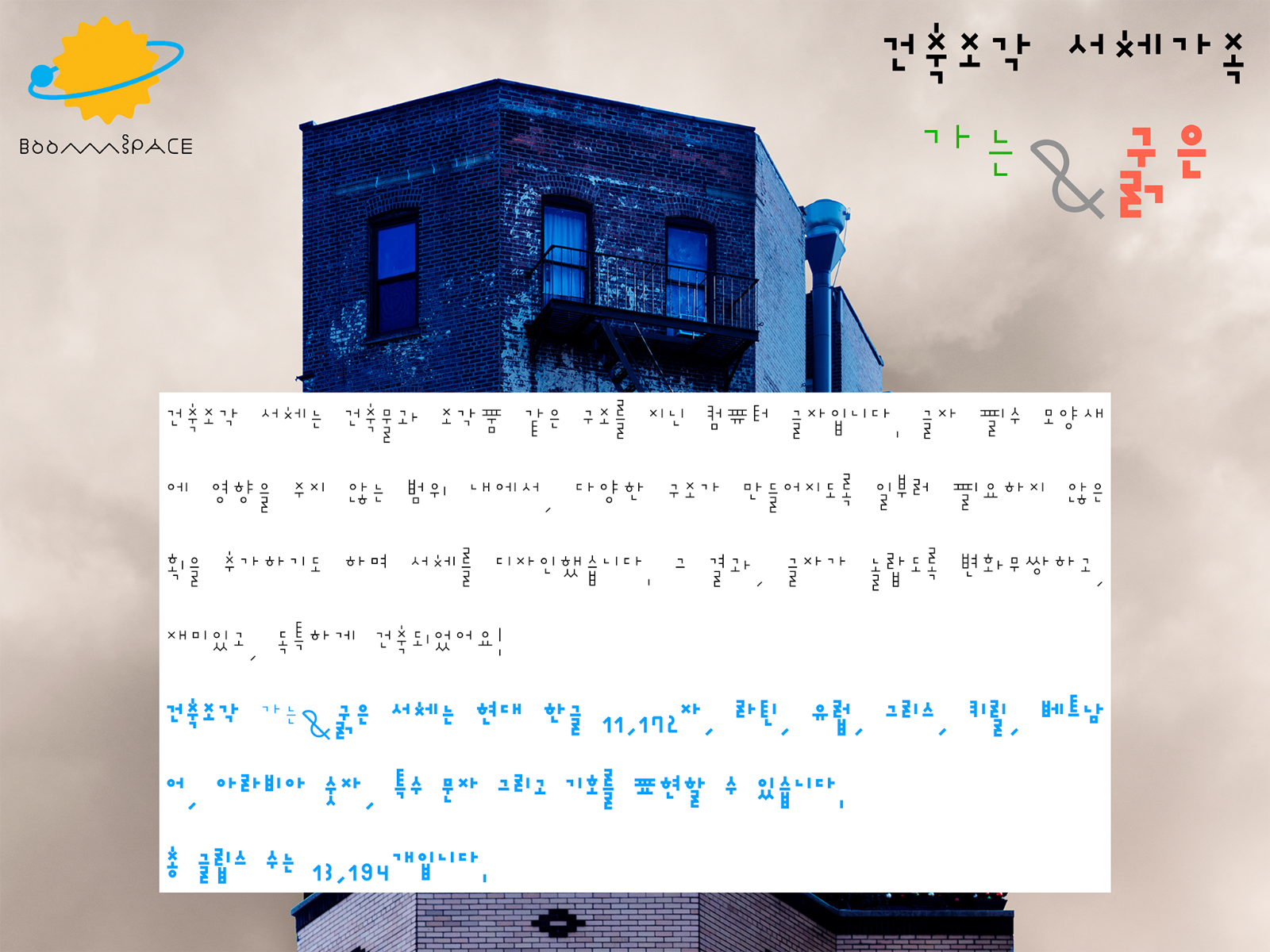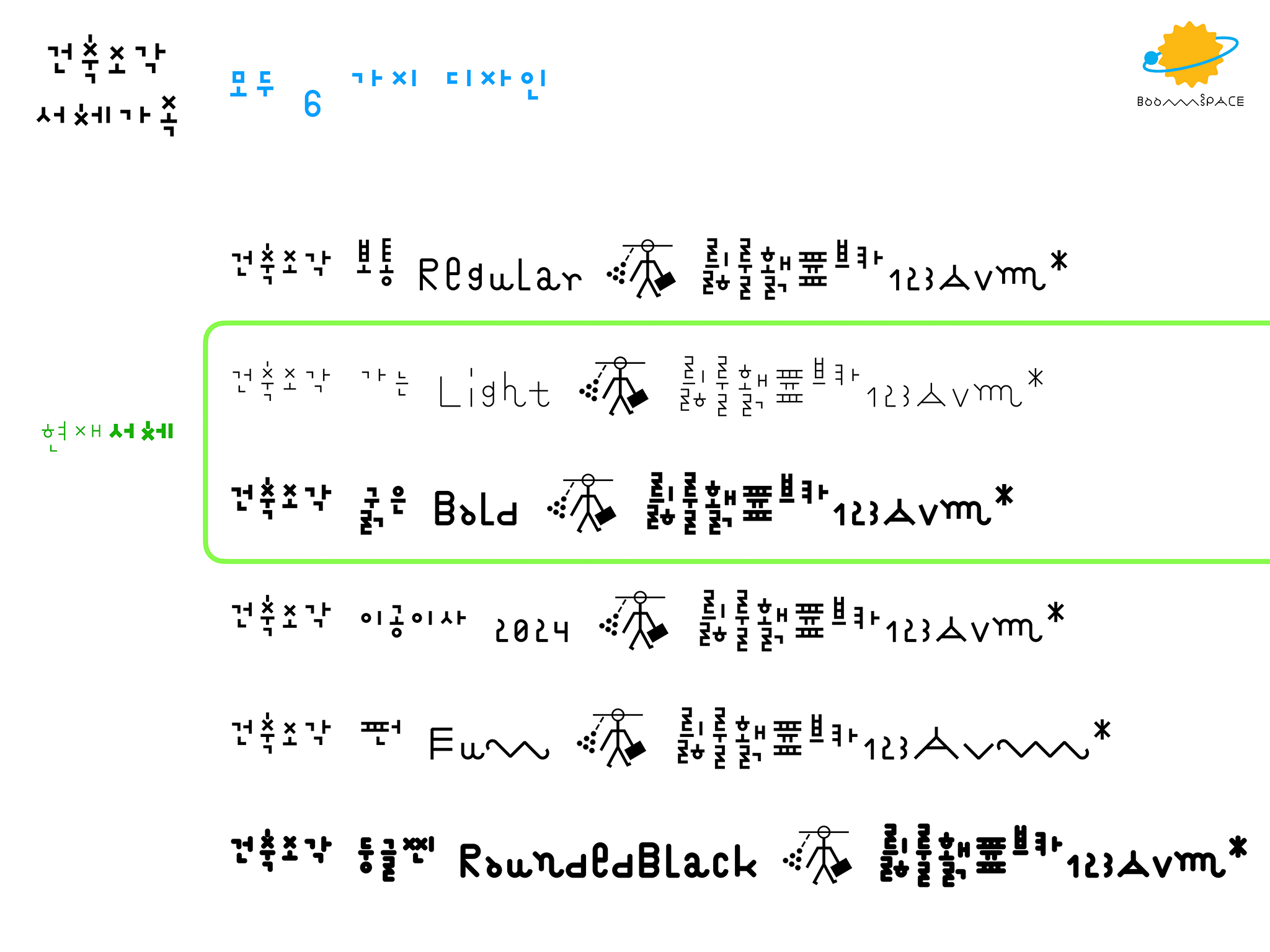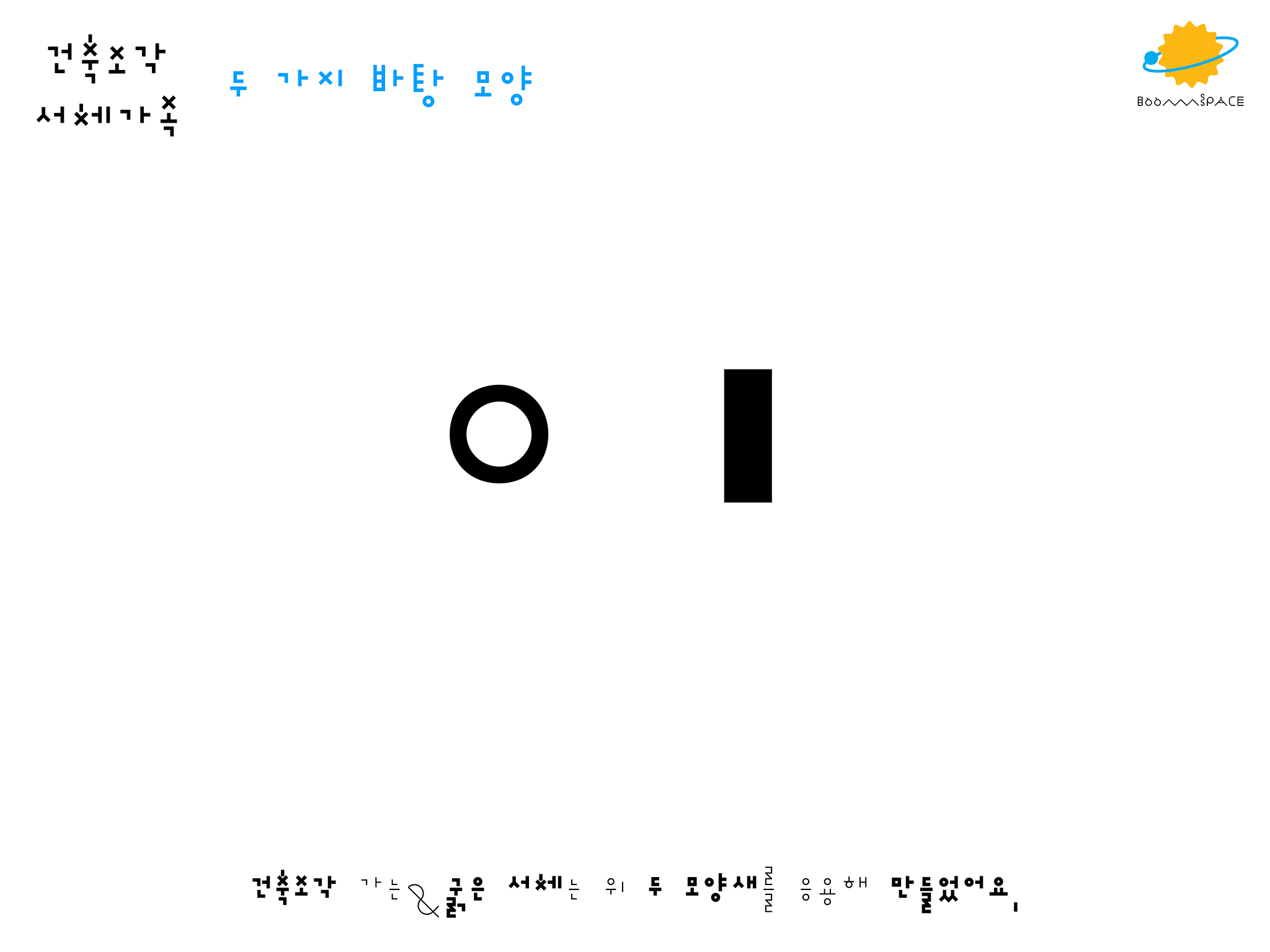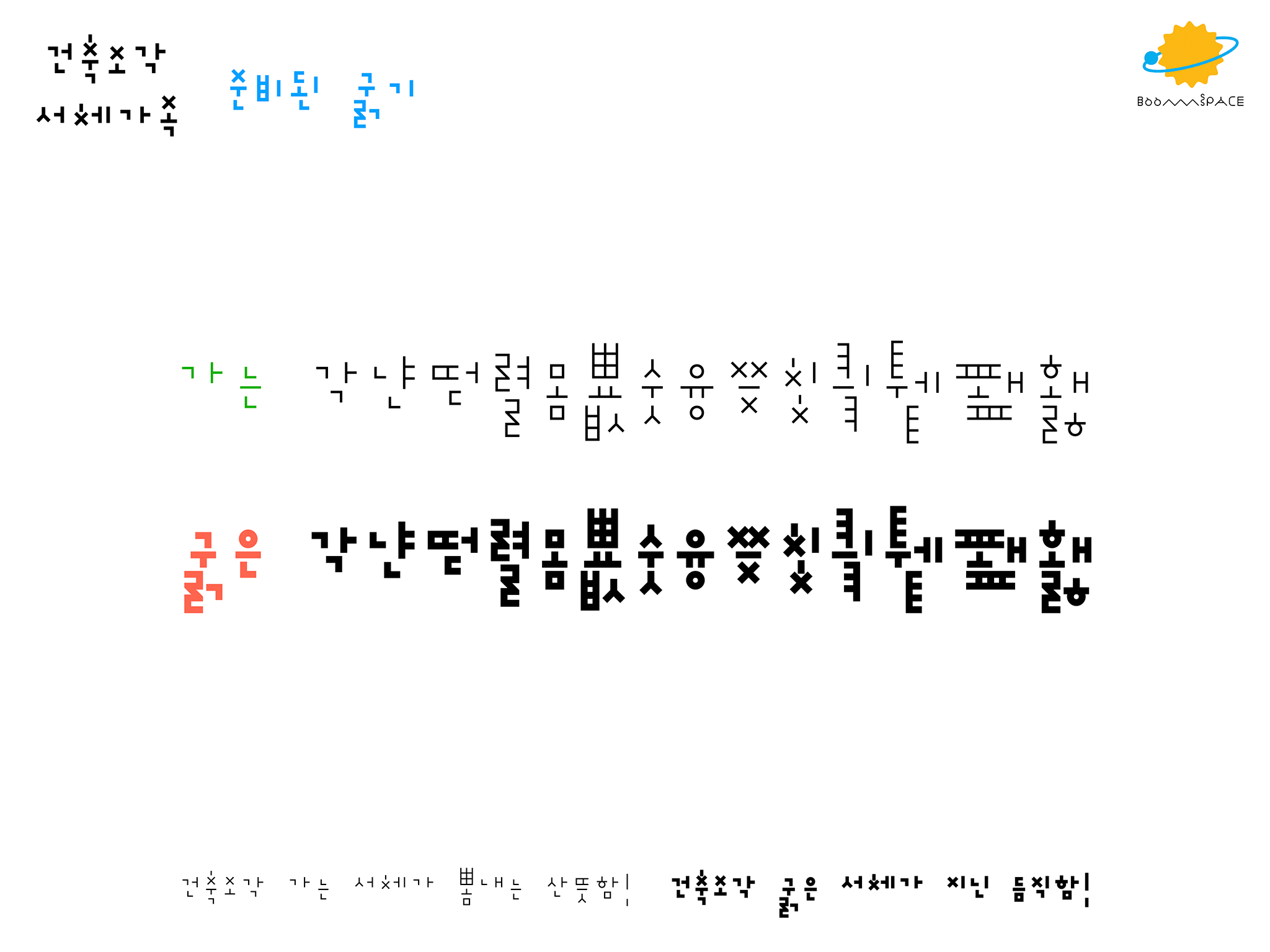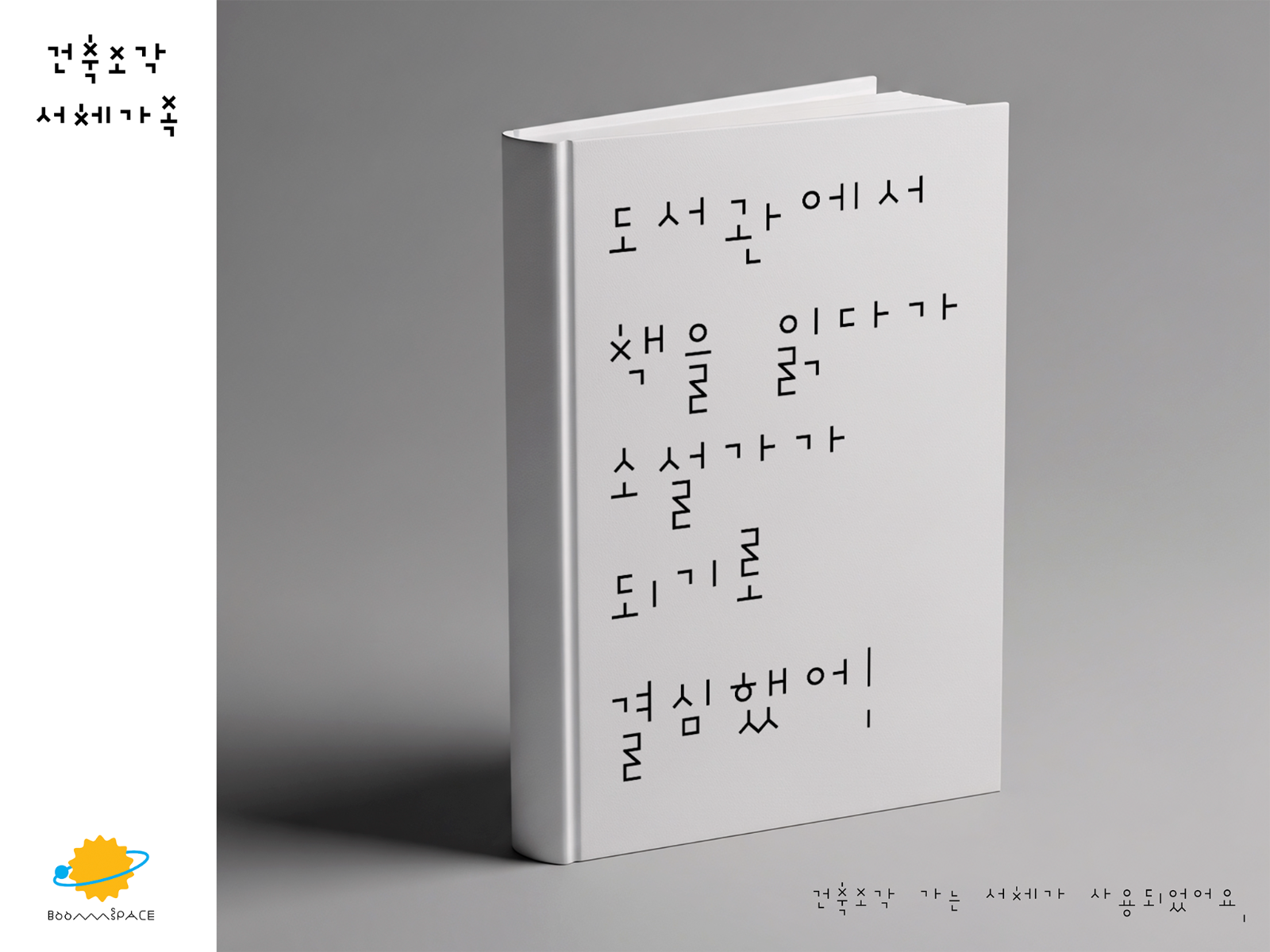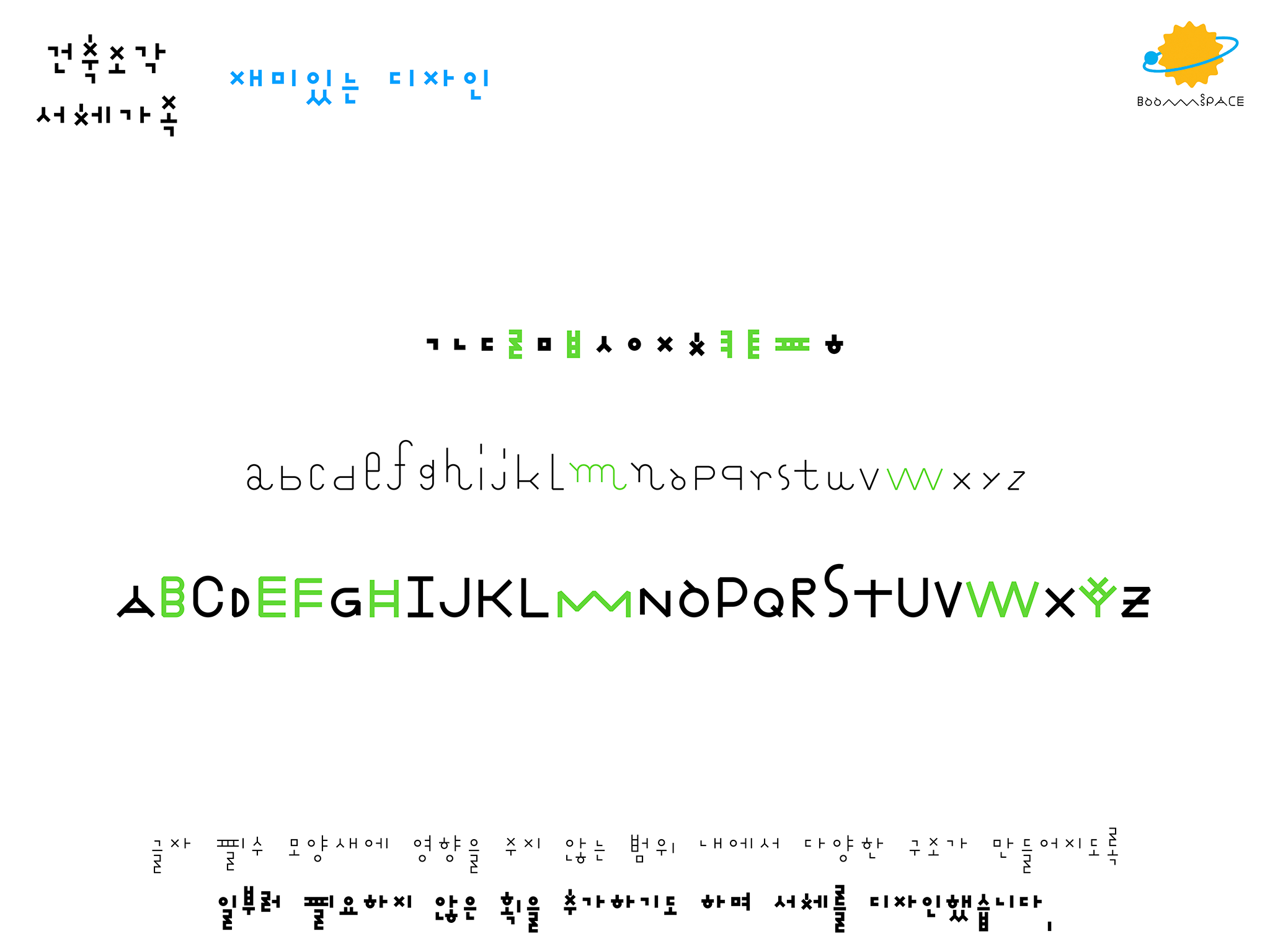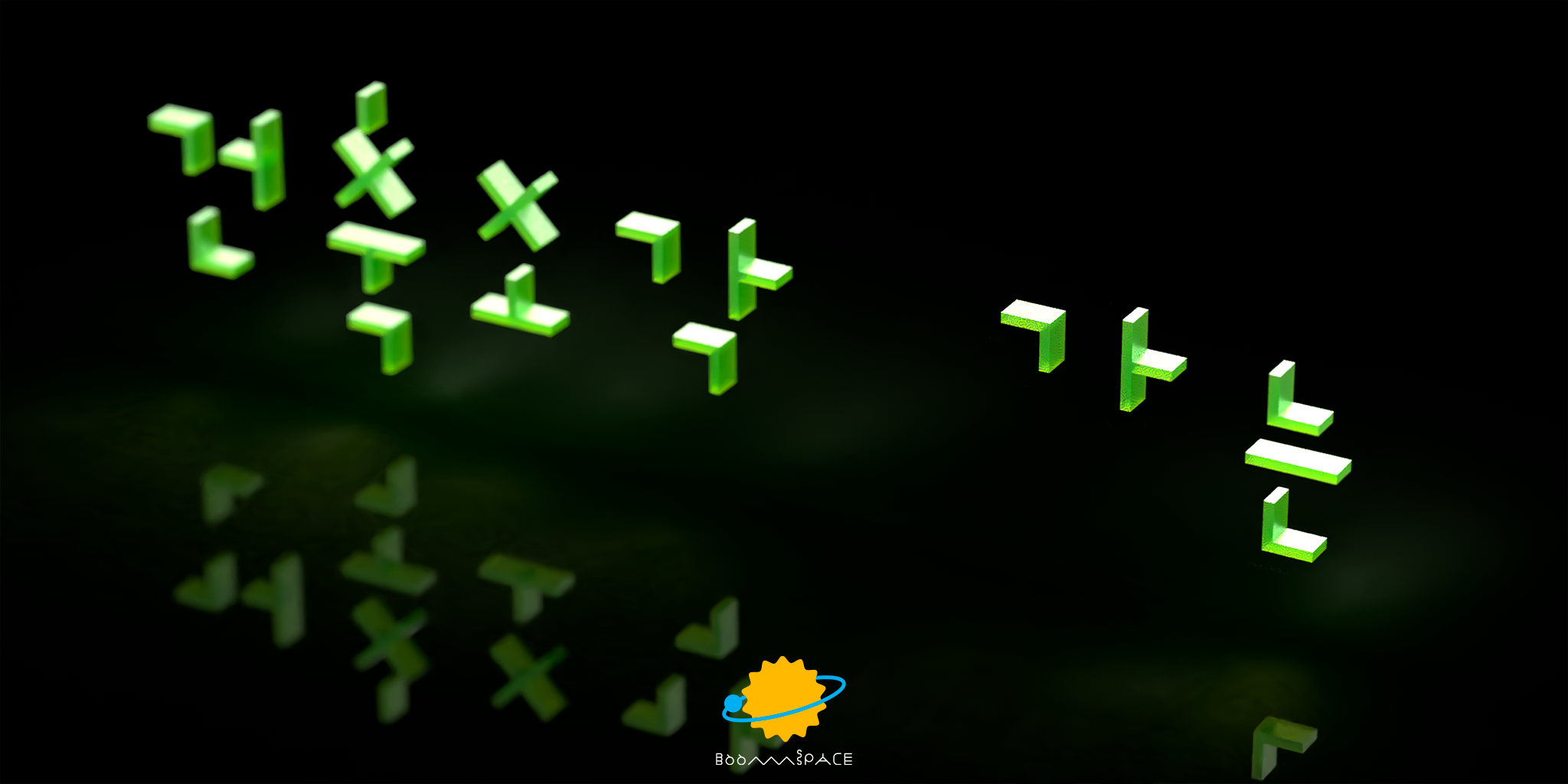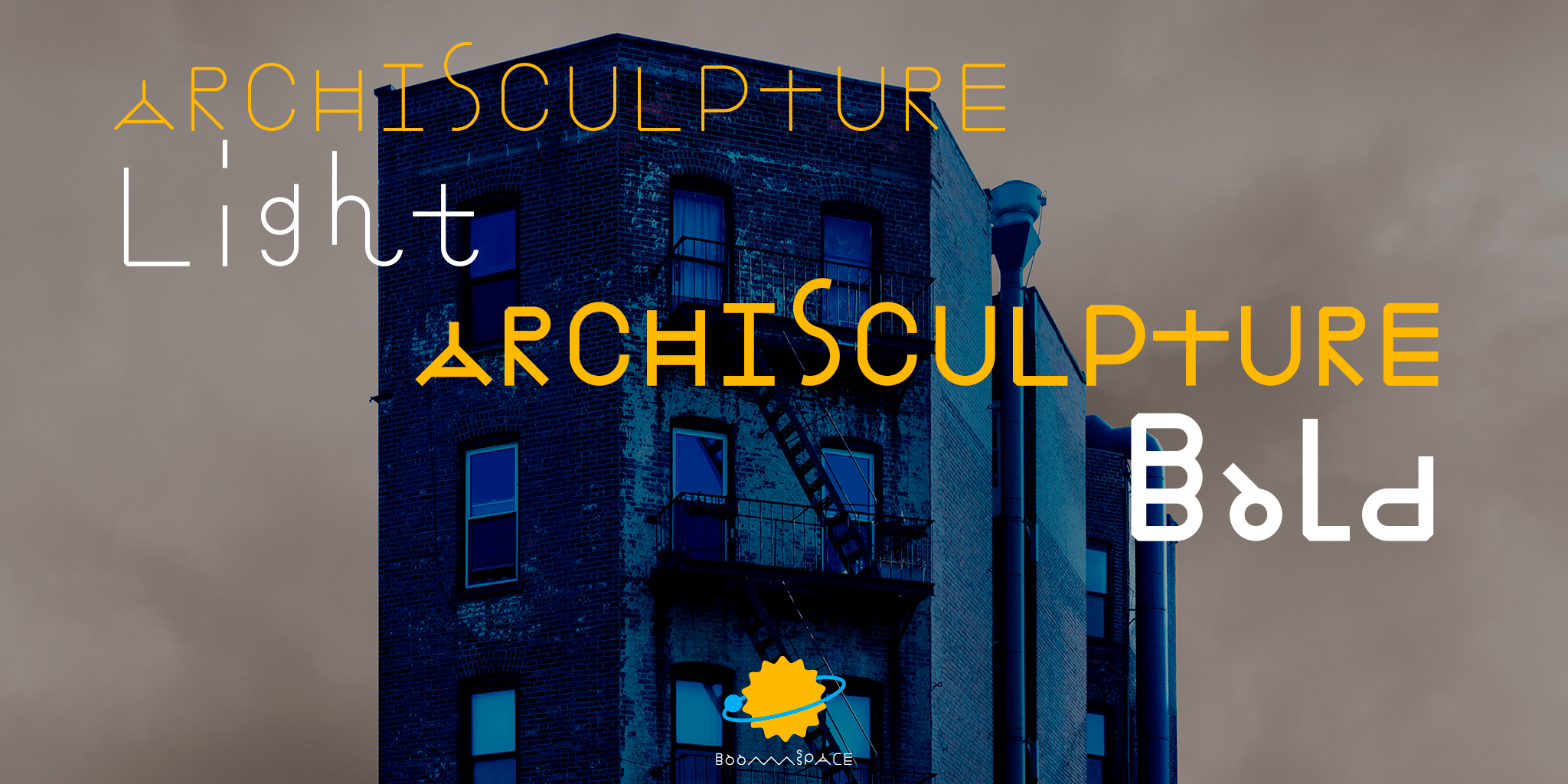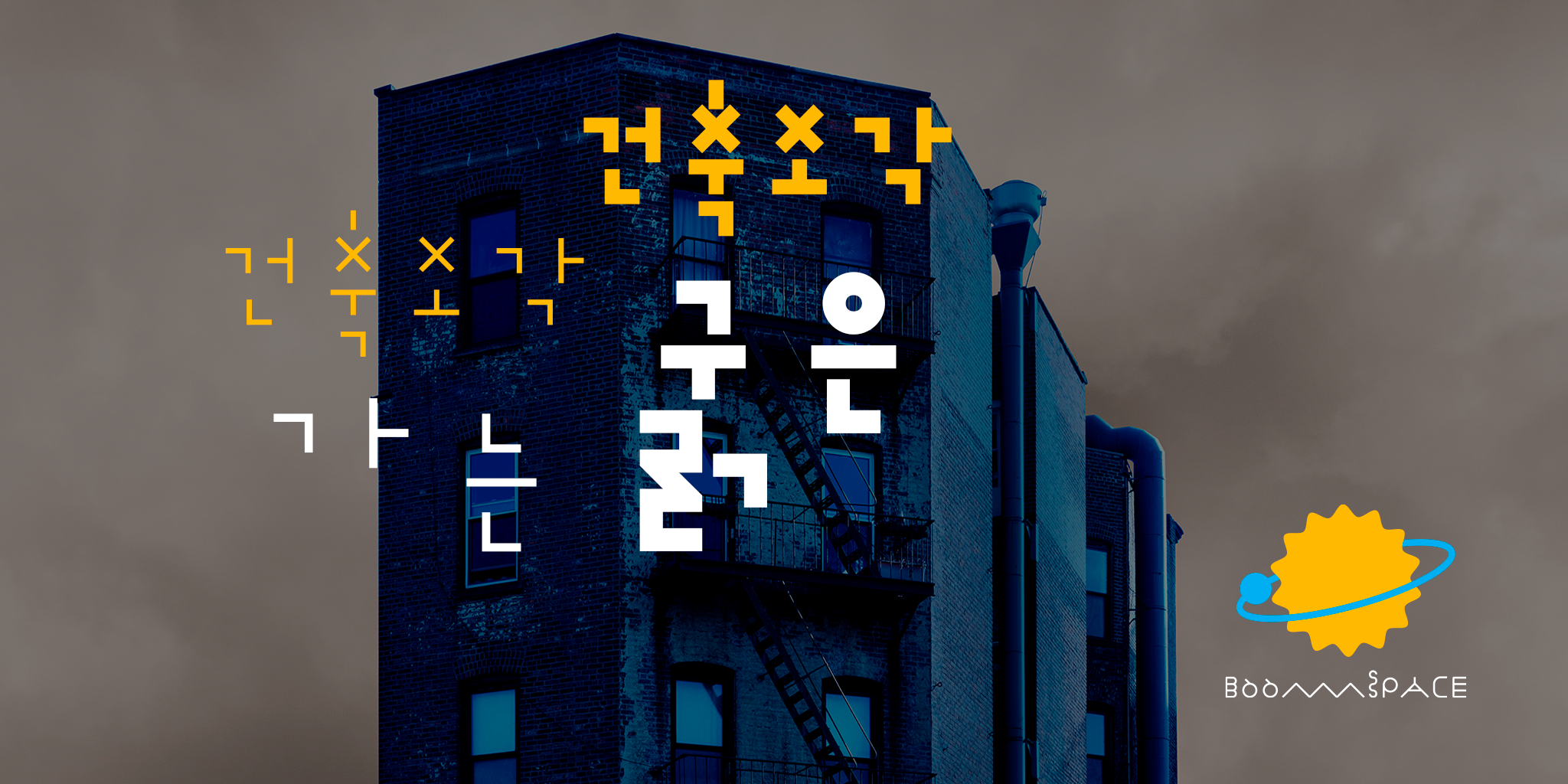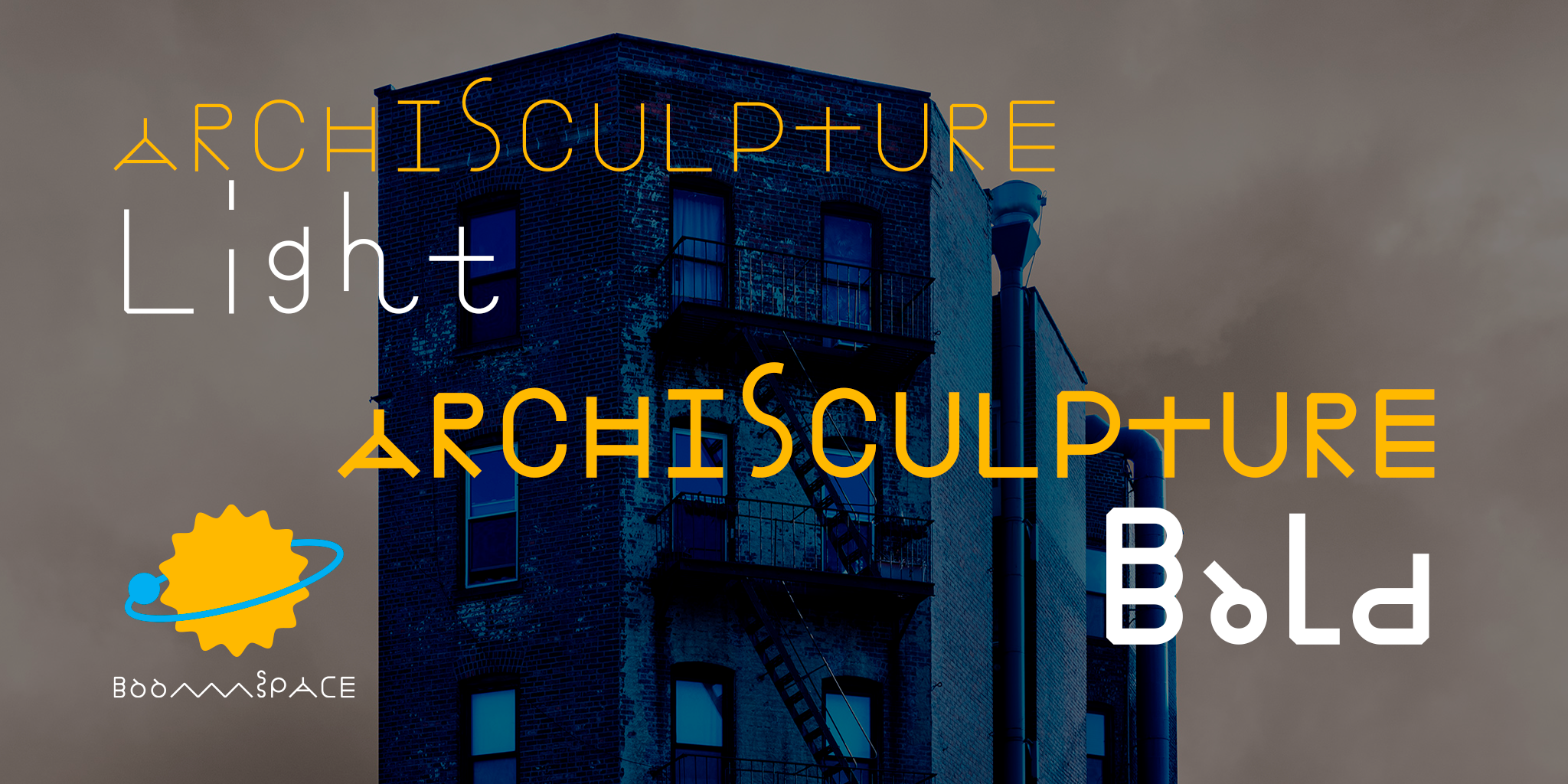
지원 글자수 한글 - 11172자
영문/숫자/기타 글리프 - 2022자
건축조각 서체는 건축물과 조각품 같은 구조를 지닌 컴퓨터 글자입니다. 글자 필수 모양새에 영향을 주지 않는 범위 내에서, 다양한 구조가 만들어지도록 일부러 필요하지 않은 획을 추가하기도 하며 서체를 디자인했습니다. 그 결과, 글자가 놀랍도록 변화무쌍하고, 재미있고, 독특하게 건축되었어요!
건축조각 첫 서체는 2022년 한글날 576돌에 발표됐어요. 다양한 건축물 사진을 콜라주해 만드는 제 건축조각 작품을 생각하며 디자인해서 이름도 건축조각 서체랍니다. [건축조각 1.0]을 처음 완성하는데 8개월이 걸렸어요. 2022년 2월부터 단순 작업을 자동화하는 기능이 없는 폰트 제작 프로그램을 사용하니까 그렇게 오랜 시간이 걸리더군요. 물론 서체 작업만 한다면 좀 더 시간을 단축했겠지만, 다른 작업과 병행하려니 계절이 두 번이나 바뀌었어요. 그나마 매킨토시 자동화 프로그램인 오토매이터가 조금 도움이 되긴 했습니다.
건축조각 가는 & 굵은 서체는 현대 한글 11,172자, 라틴, 유럽, 그리스, 키릴, 베트남어, 아라비아 숫자, 특수 문자 그리고 기호를 표현할 수 있습니다. 총 글립스 수는 13,194개입니다.
독특한 건축조각 서체로 멋진 글과 디자인 작품을 지어보세요!
건축조각 가는 & 굵은